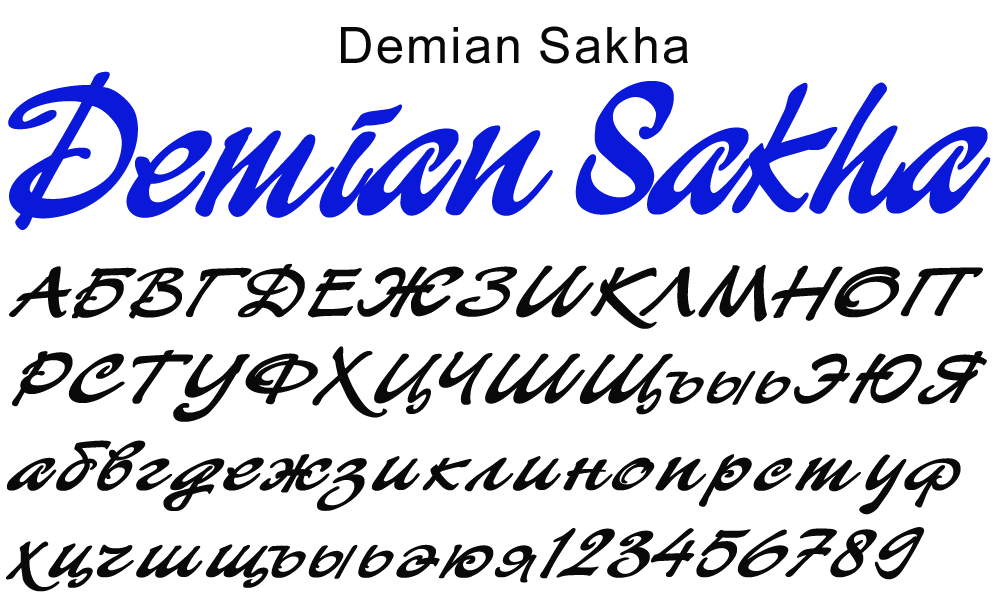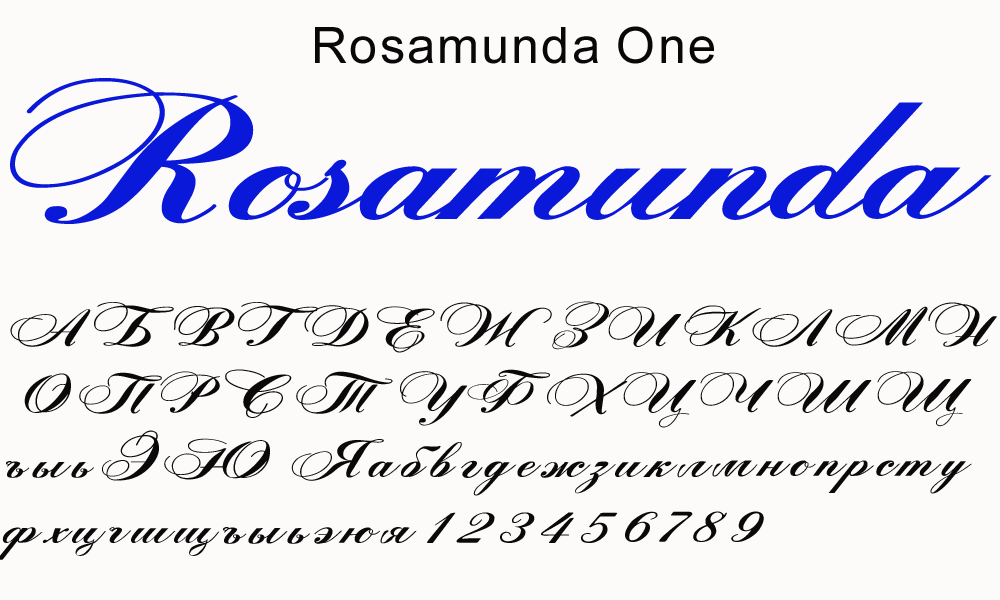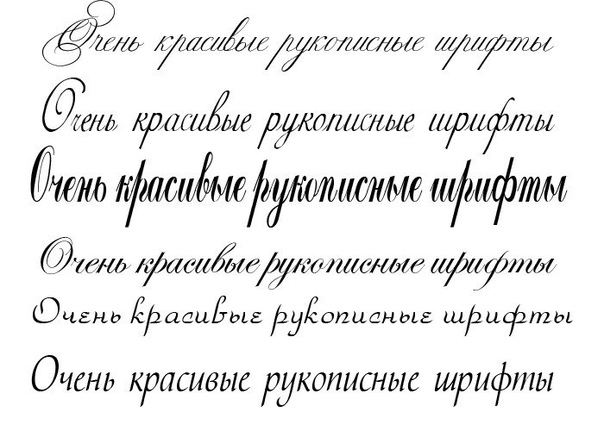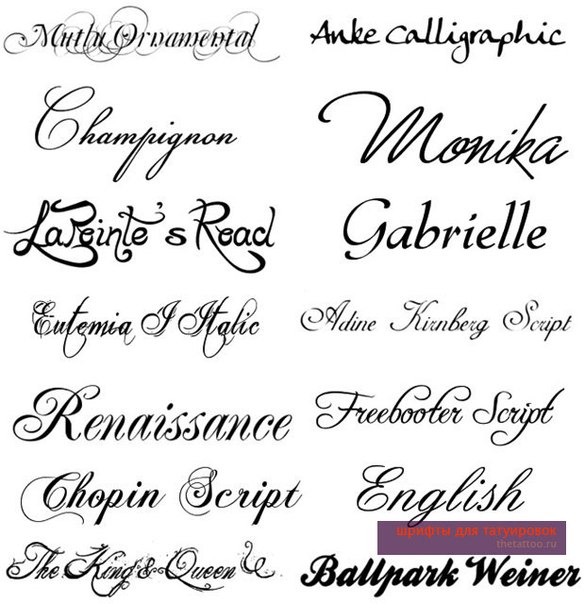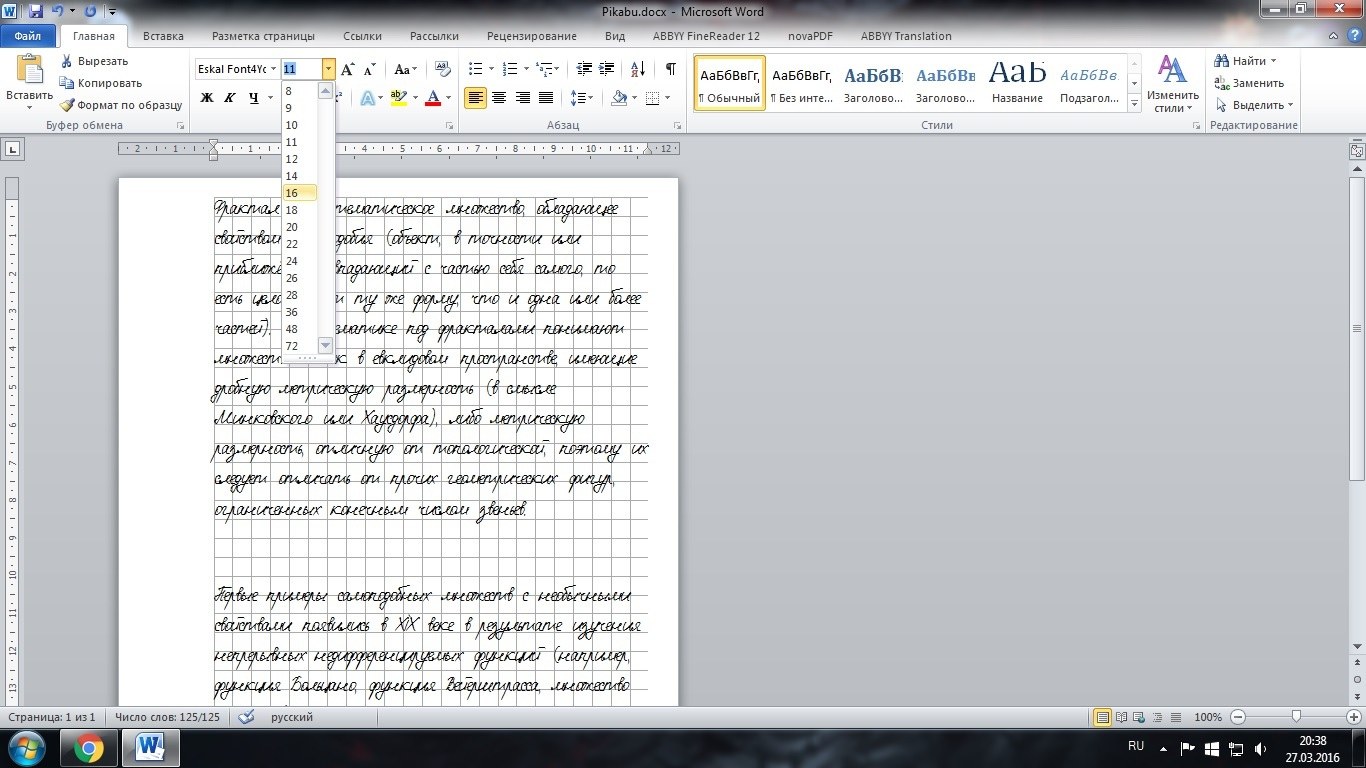
Шрифт рукописный ворд: Русские рукописные шрифты для Word, скачать рукописные шрифты
Рукописные, прописные шрифты (Handwritten, Script fonts) на BestFonts.pro
Скрипты имитируют написанные от руки буквы, цифры и другие символы. Именно этим объясняется их название. Шрифты востребованы в веб-дизайне и вёрстке макетов для печати. Вид шрифтовых наборов определяется по имитируемому инструменту для письма. Например, ширококонечное перо, художественная кисть, графитовый карандаш, спиртовой фломастер или обыкновенная ручка.
Дополнительно рукописные шрифты делятся на связные и несвязные. В первом случае буквы соединяются между собой, а во втором символы стоят в строках отдельно.
Существуют и полусвязные шрифты. Объединение выполняется по конкретным частям или сторонам знаков. Что касается области применения, то к шрифтовым комплектам часто прибегают для привлечения внимания или оформления учебников.
К минусам шрифтов относят затруднённое визуальное восприятие, что снижает удобство чтения набранных текстов. Зато скрипты превосходно подходят для придания значимости заголовкам, цитатам, отдельным строкам или маленьким отрывкам классических литературных произведений. С их помощью часто оформляют ресторанные меню, логотипы фирм, коммерческие презентации, названия глав и т. п.
По начертанию шрифты делятся на несколько больших групп. Формальные скрипты основываются на литерах из книг писателей 17-18 веков. Написание стилизуется под выведенные пером буквы. Толщина линий – равномерная. Наборами пользуются, когда необходимо сымитировать рукопись и пропись или оформить грамоты и приглашения на торжественные события вроде свадеб и юбилеев.
Вторая группа – казуальные шрифты, которые воспроизводит мокрую кисть, отличаются свободным начертанием и иногда имеют линии с переменной толщиной.
Подборка из 20 рукописных шрифтов, латиница
Новая большая подборка рукописных шрифтов, шрифтов которые выглядят как ручной леттеринг. Подборка шрифтов от разных дизайнеров со всего мира в разных стилях. На этот раз мы подобрали 20 шрифтов которые можно скачать бесплатно, и использовать в своих личных целях, только не для коммерции. Предыдущую подборку вы можете скачать тут.